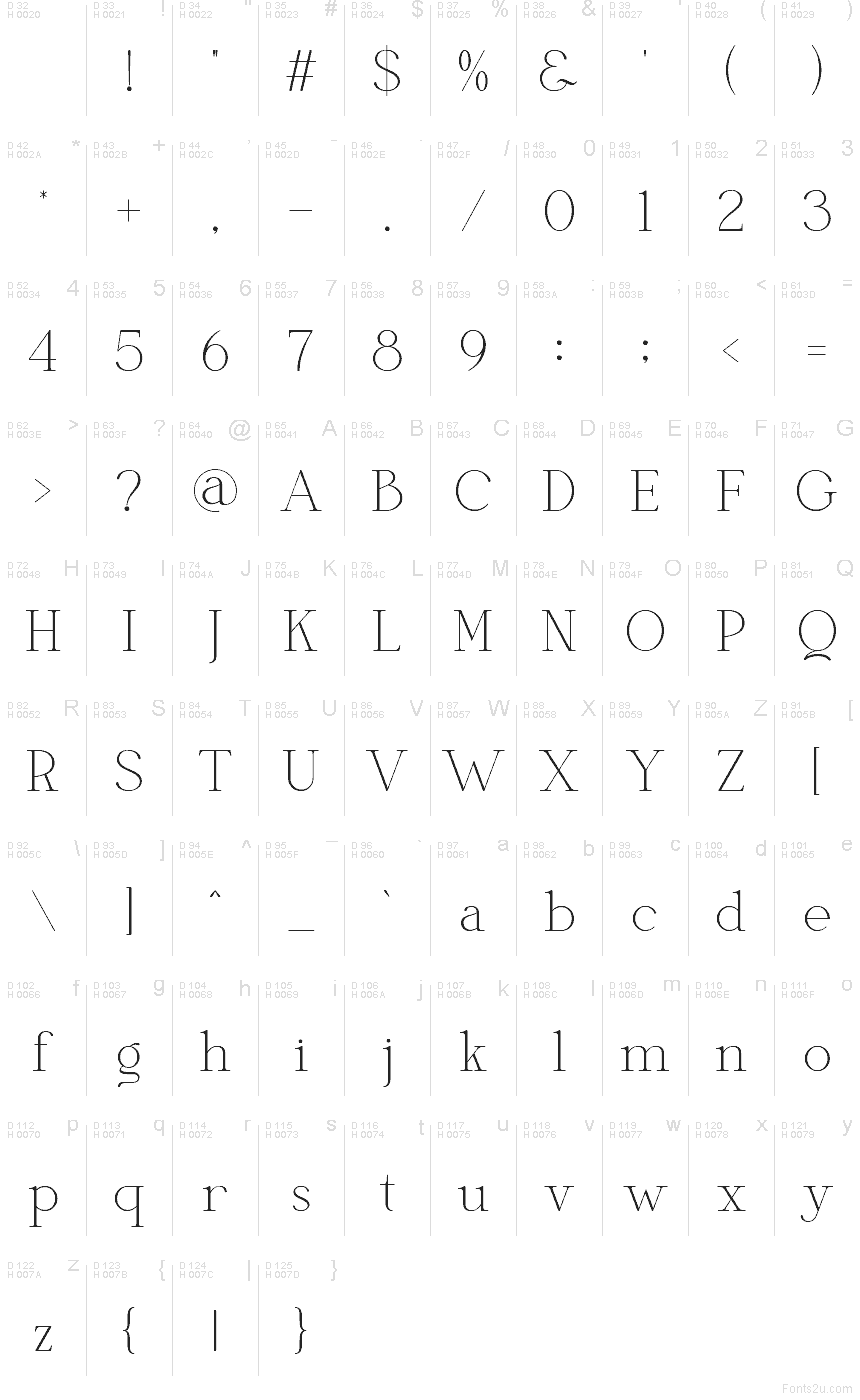
Qariga, da Ermedia Studio, é uma fonte com serifa gratuita que apresenta proporções alongadas e traços excepcionalmente finos. Suas curvas amplas mantêm as letras abertas e arejadas. A diferença entre as barras transversais ultrafinas e as hastes verticais mais espessas é pronunciada, acompanhada por serifas delgadas que se prolongam suavemente a partir das letras.
O design de revistas de moda é um uso convincente para essa tipografia delicada e de alto contraste, especialmente em títulos de destaque. Sua elegância contida também se harmoniza com embalagens de perfumes e convites formais. Em todas essas composições, a combinação de curvas amplas e linhas finas oferece uma alternativa sofisticada às serifas tradicionais mais encorpadas.